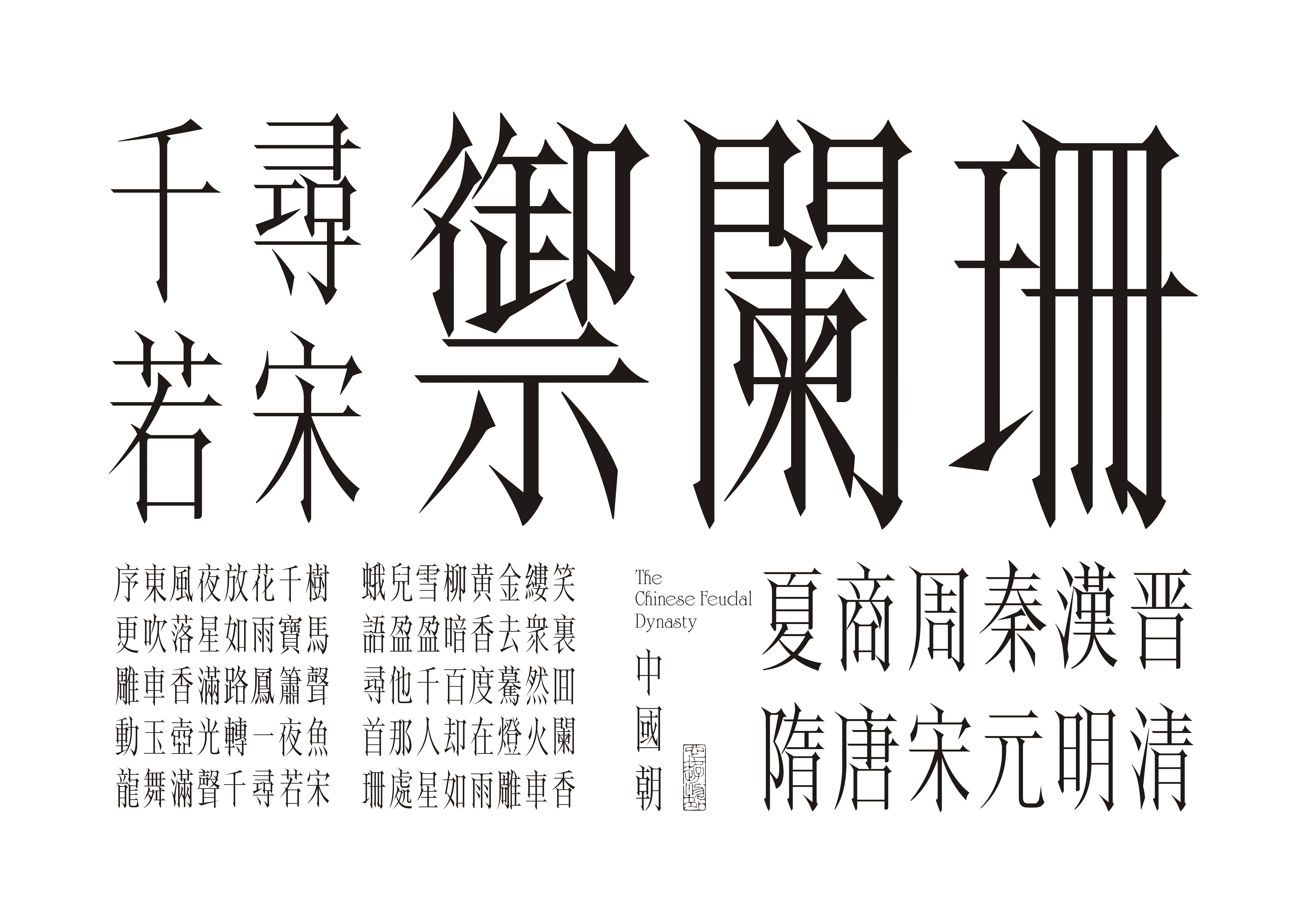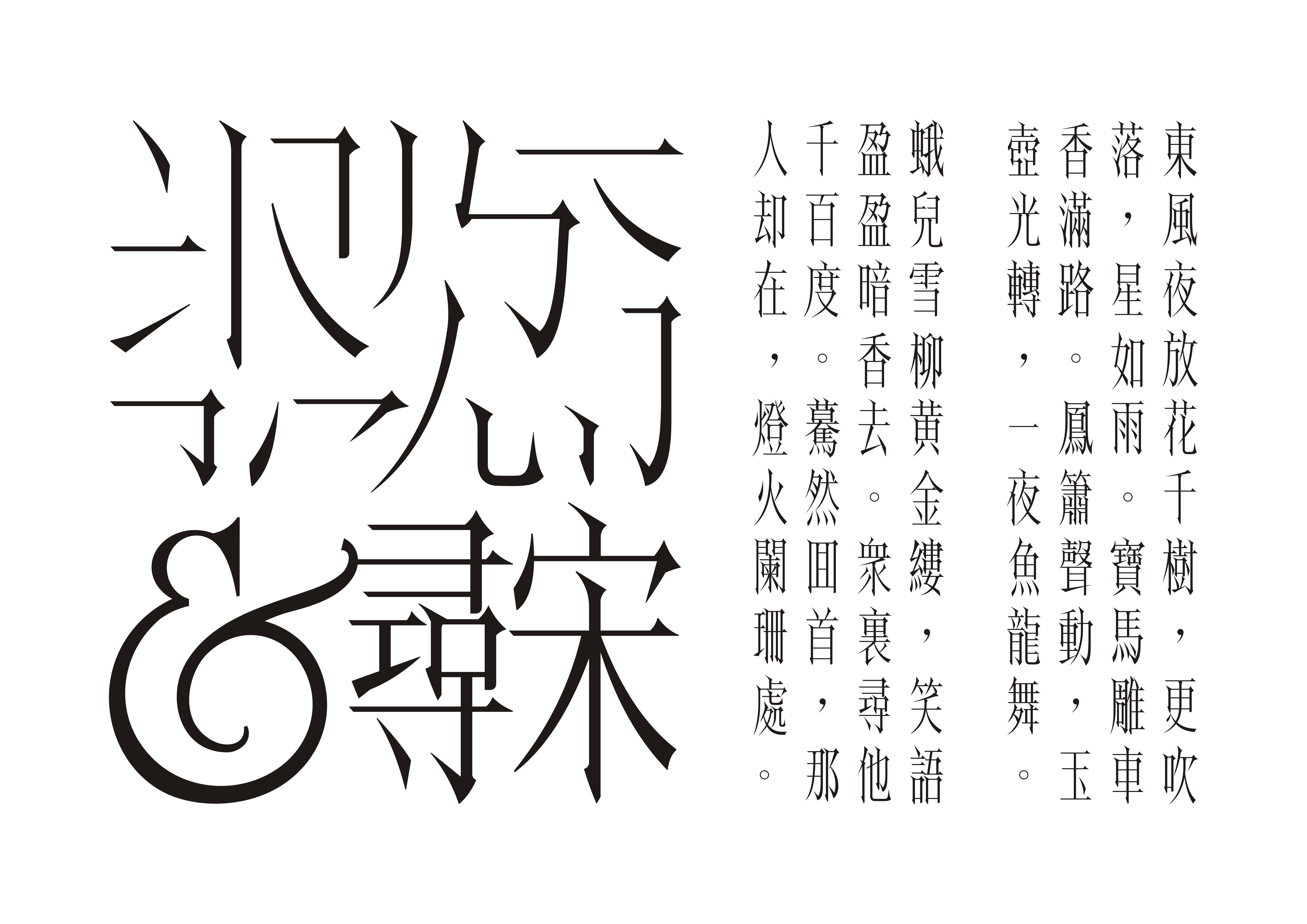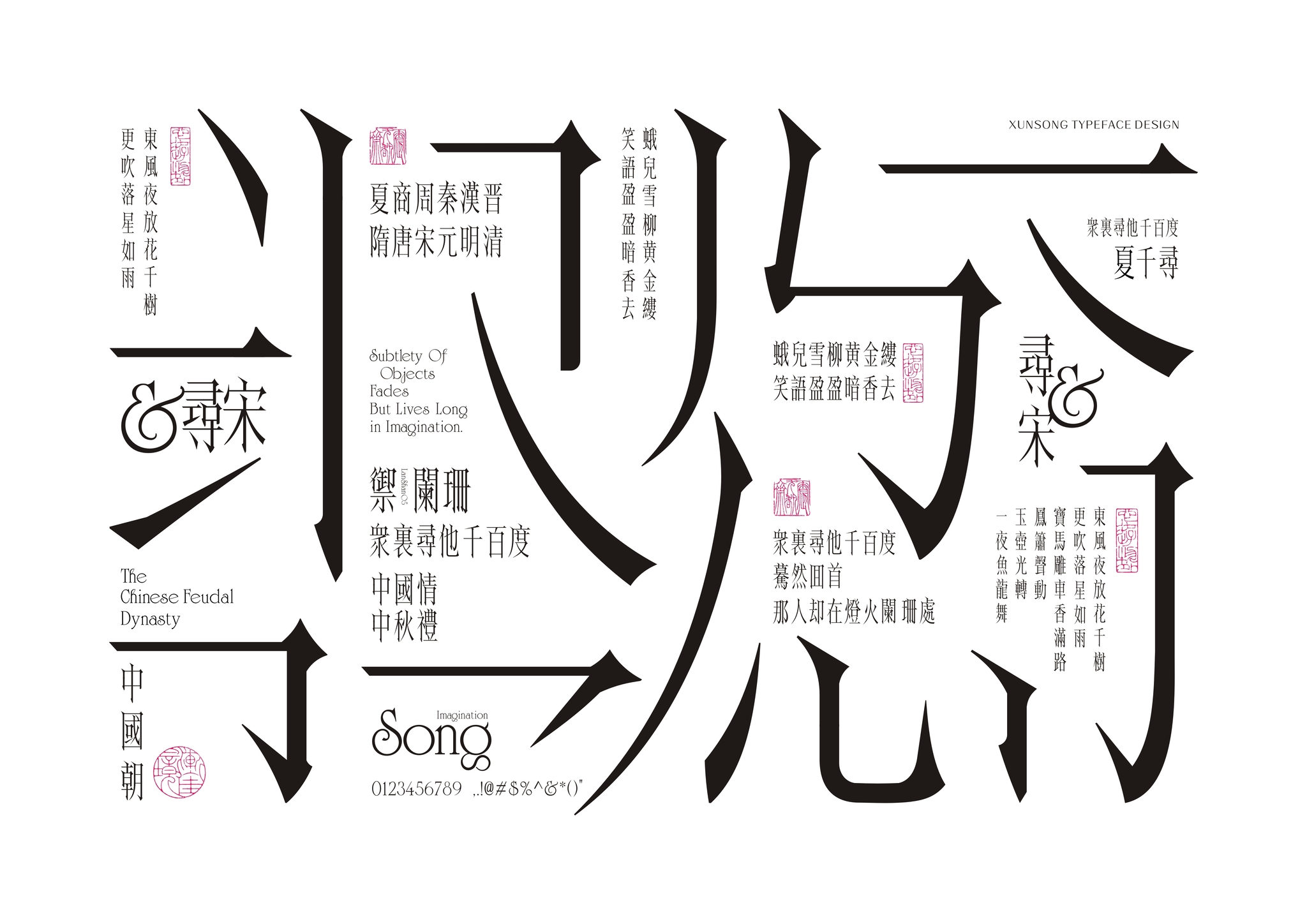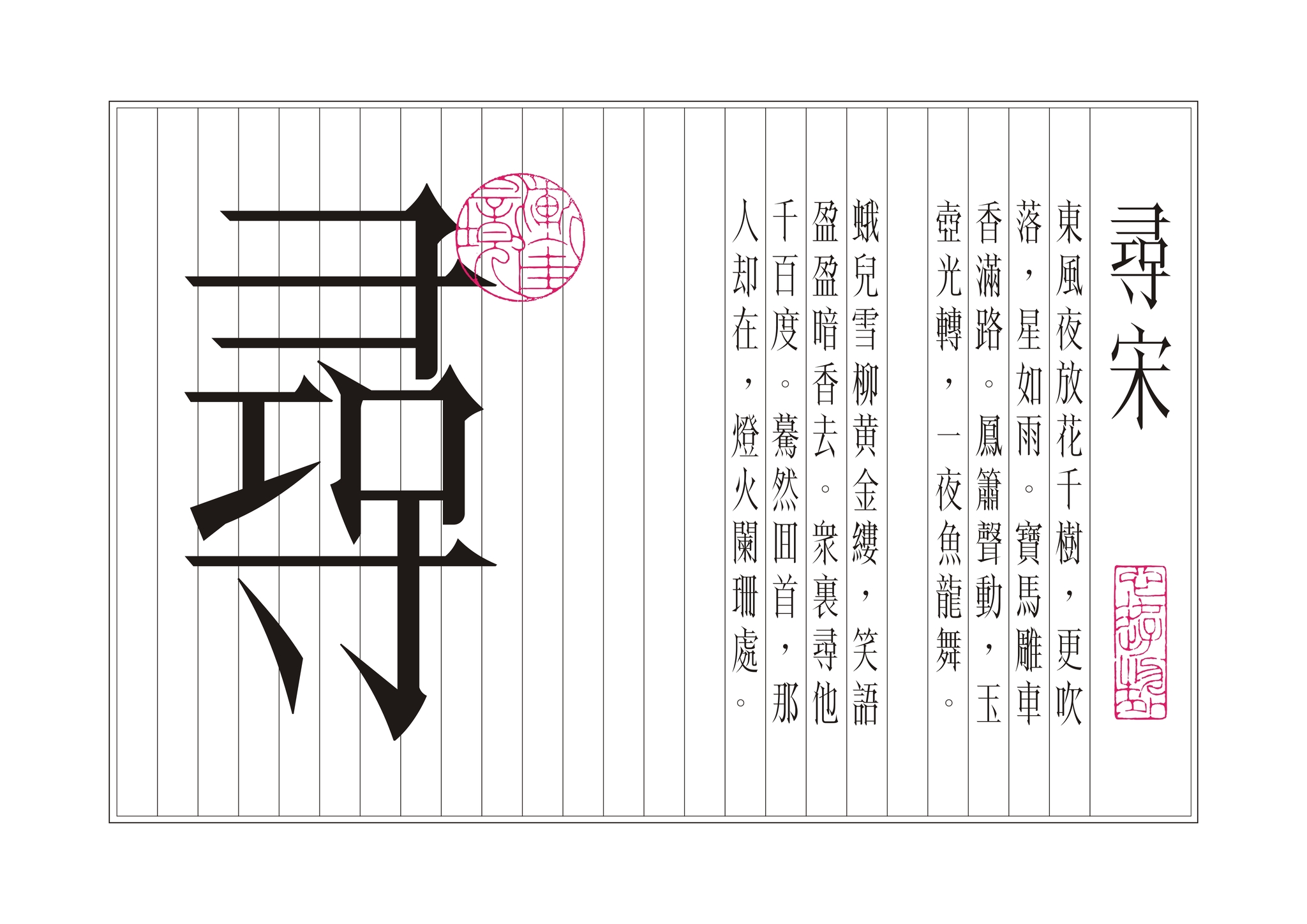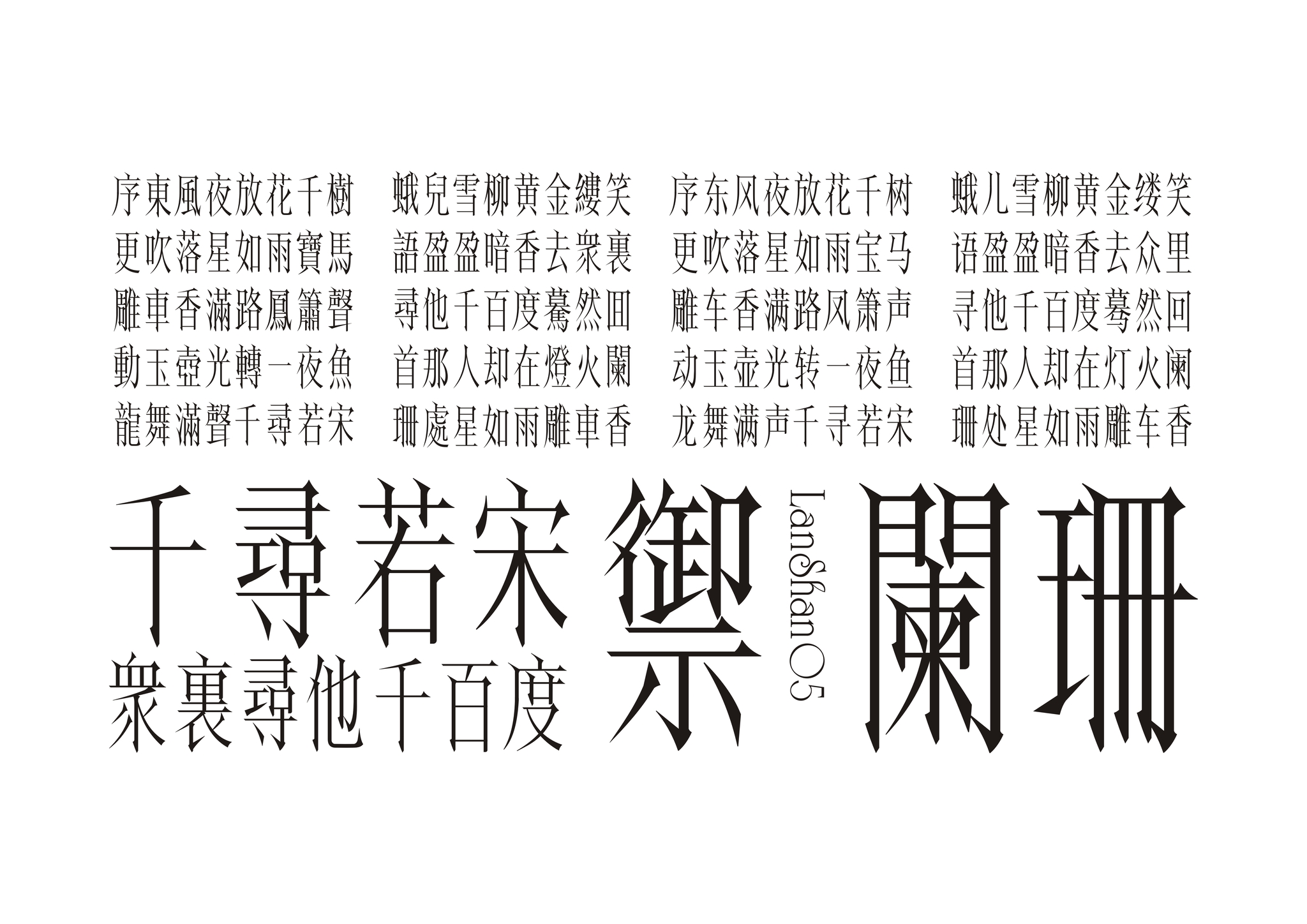
Font Design on Xun-Song Typeface
Inspirada en la tipografía Imitation Song y Slender Gold (representada por el emperador Huizong), la creación emana una dinámica de caligrafía de pluma dura y pincel suave, muy diferente de la tradicional Imitation Song. Aquí, los trazos horizontales van rectos todo el tiempo, uniformes en grosor. Con una dinámica afilada, son una mezcla de firmeza y flexibilidad, compactos y delicados. Los comienzos y los finales presentan adornos como serifas. Sus trazos en punto, izquierda-caída, derecha-caída, gancho y más son afilados y finos, de aspecto elegante y vibrante. Con letras, símbolos y números latinos, son retro, ligeras y modernas, ideales para imprimir en papel.